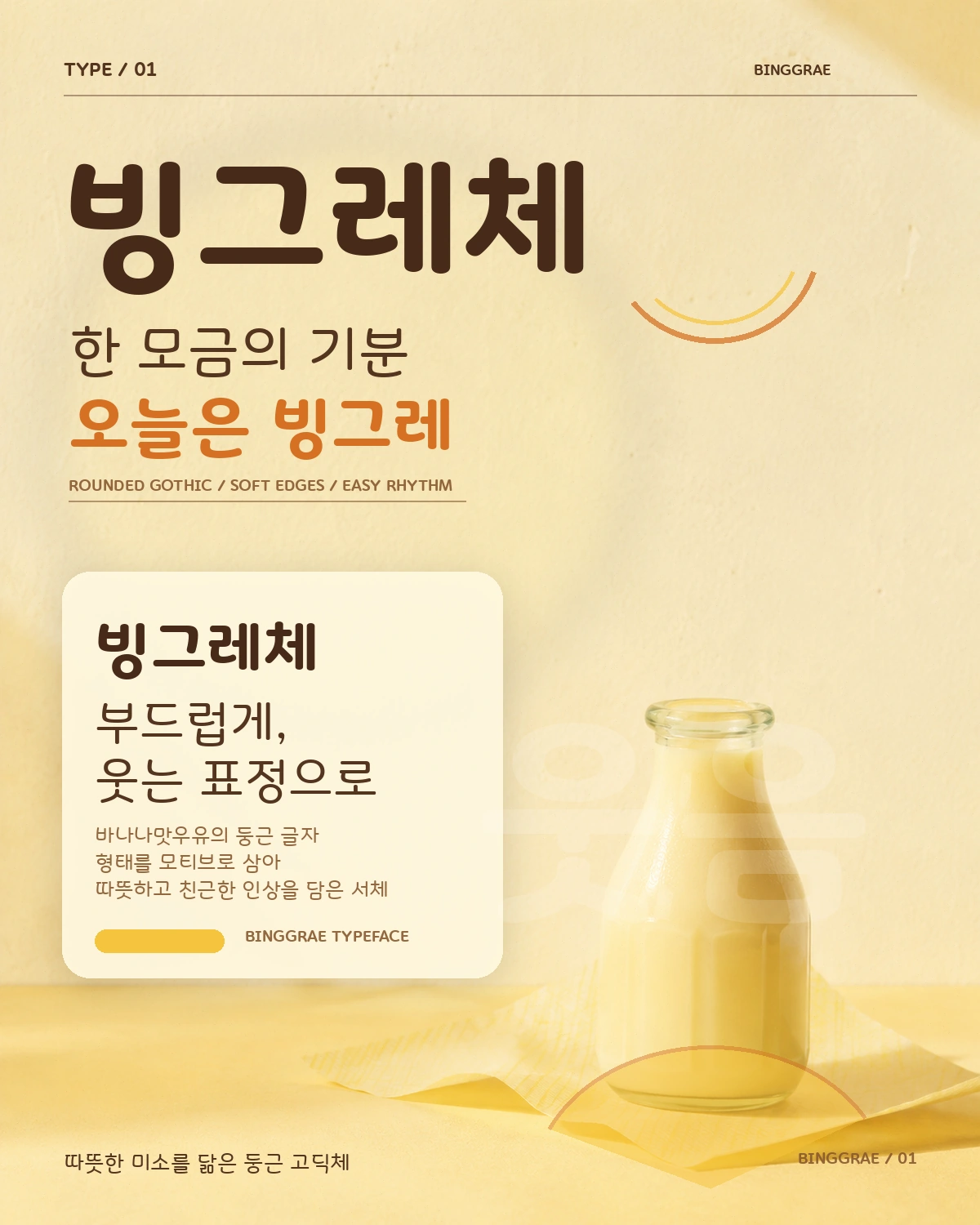
빙그레체 무료폰트
빙그레체 — 빙그레에서 배포하는 무료 폰트입니다. 바나나맛우유의 글자 형태를 모티브로 삼아, 따뜻한 미소를 닮은 인상을 만든 둥근 고딕체
빙그레가 2016년 한글날 즈음에 공개한 서체입니다. 창립기념일이 한글날과 같은 10월 9일이라는 점이 개발의 계기가 됐고, 2015년 10월 세종대왕기념사업회 등과 협약을 맺은 뒤 약 1년 만에 완성했습니다. 모티브는 바나나맛우유의 글자 형태입니다.
제작사가 밝힌 설계 원리가 특이합니다. 훈민정음 창제 원리에 입각해 디자인했고, 초성과 중성, 종성을 분리해 판독성을 높였다는 것입니다. 실제로 파일을 재어 보면 받침이 붙을 때 글자 높이가 눈에 띄게 달라지는 탈네모틀 구조인데, 자소를 독립적으로 다뤘다는 설명과 맞아떨어집니다. 조형 요소로는 부드러운 곡선의 꺾임, 획의 시작과 끝의 굴림, 정원 형태의 ㅇ꼴, ㅈ과 ㅊ의 세운 꼭지와 세 획 형태를 꼽습니다.